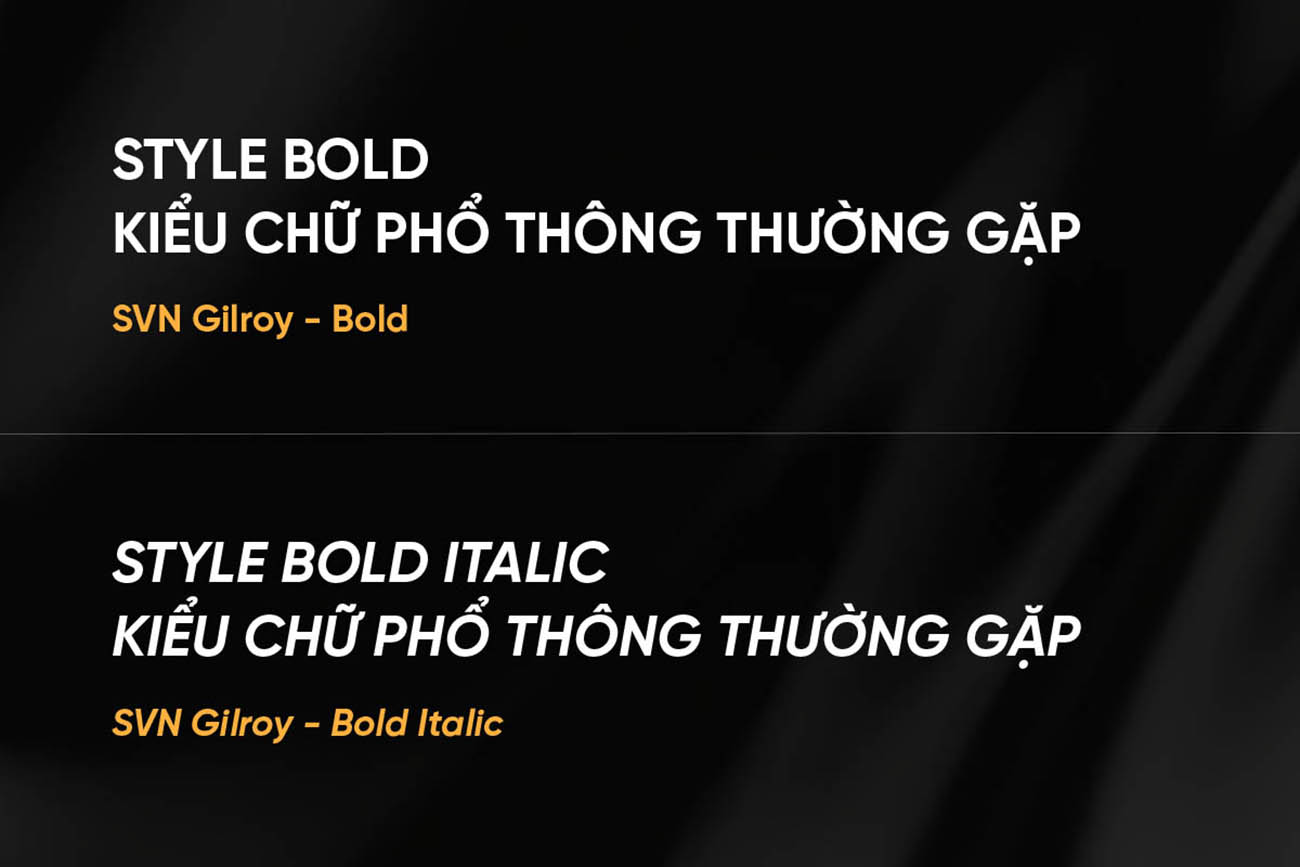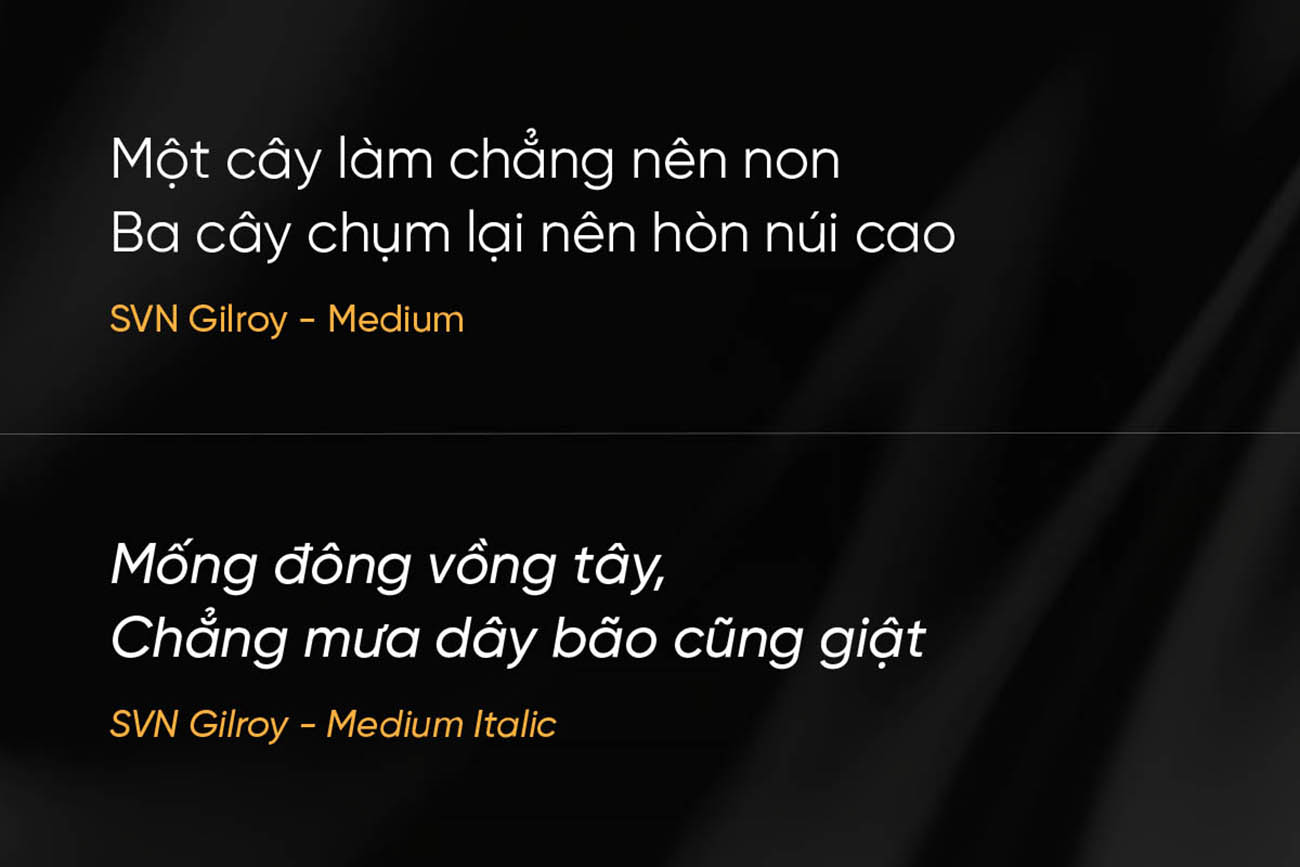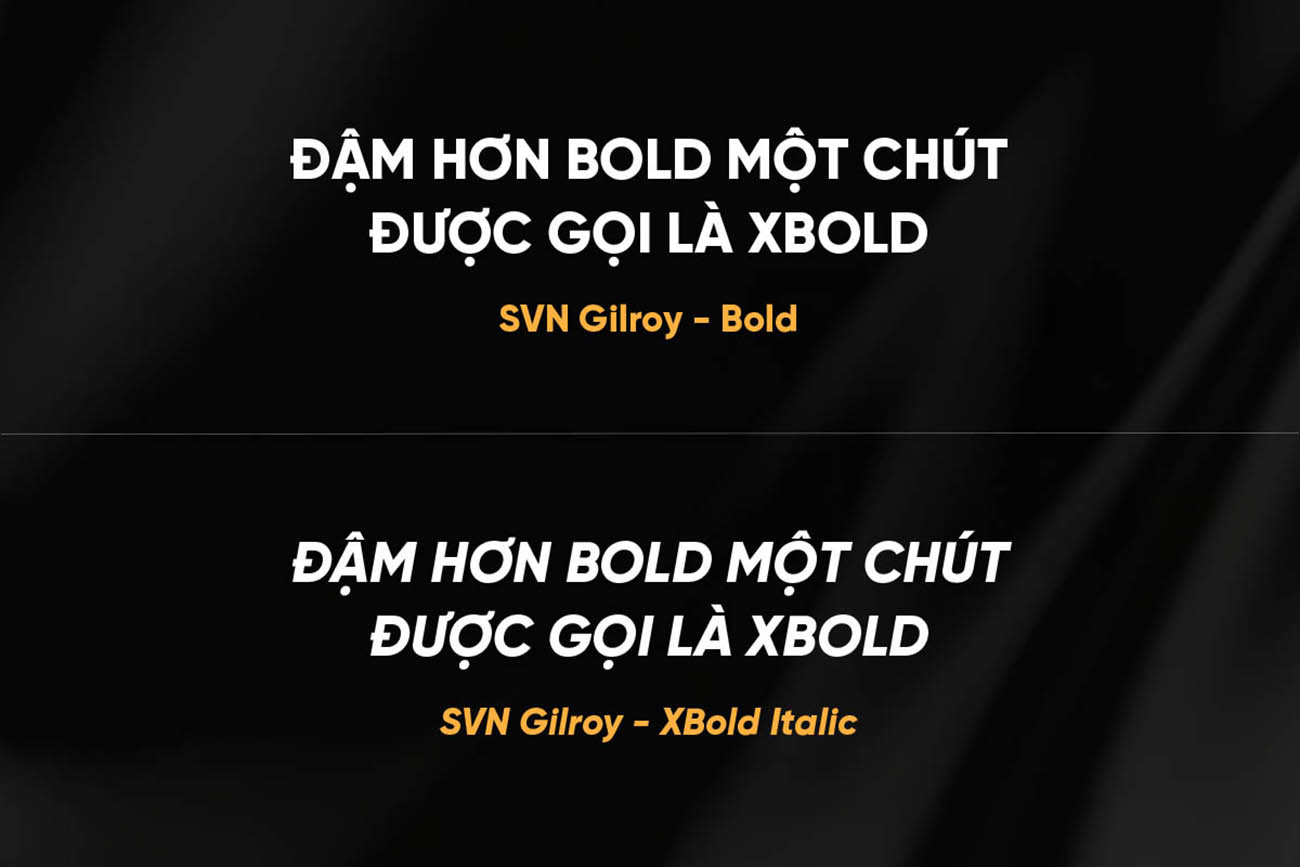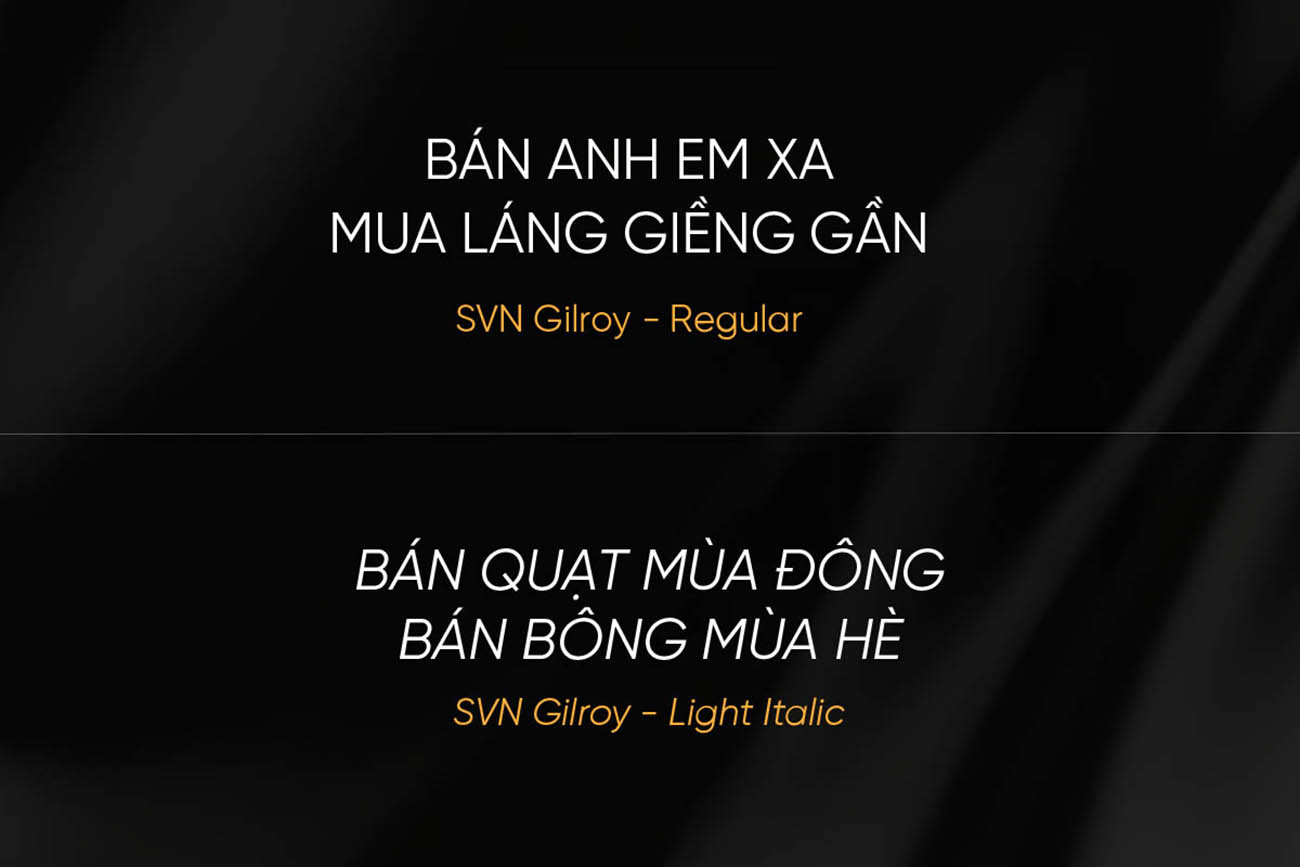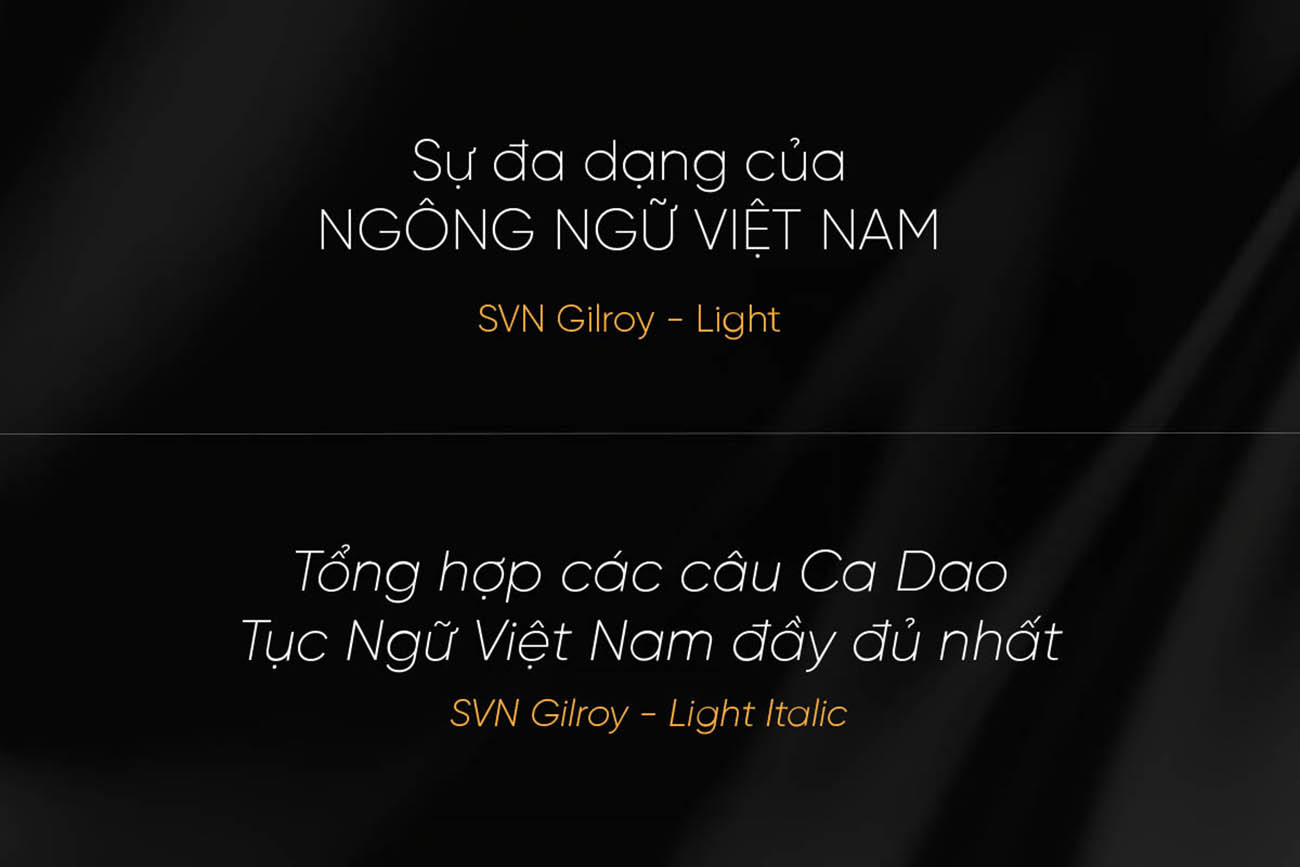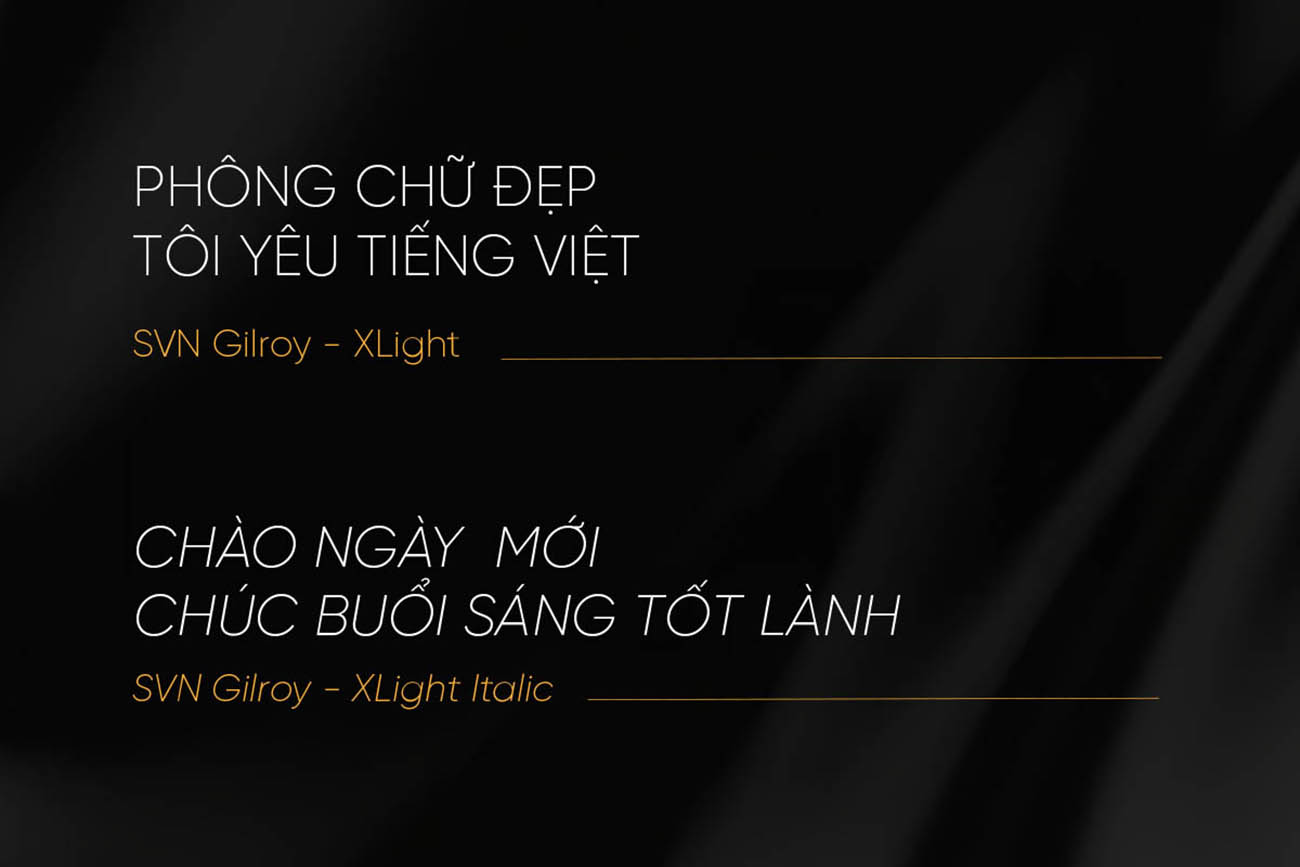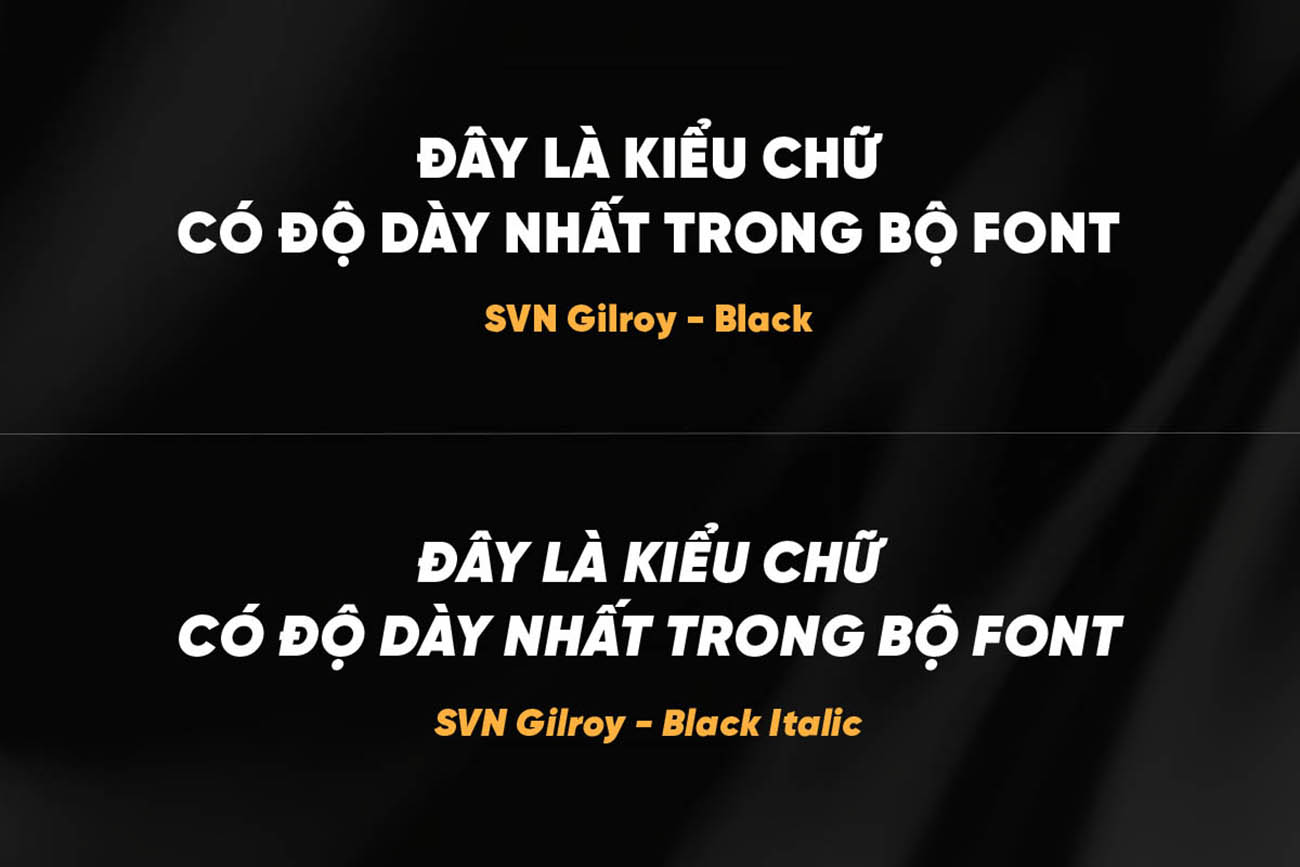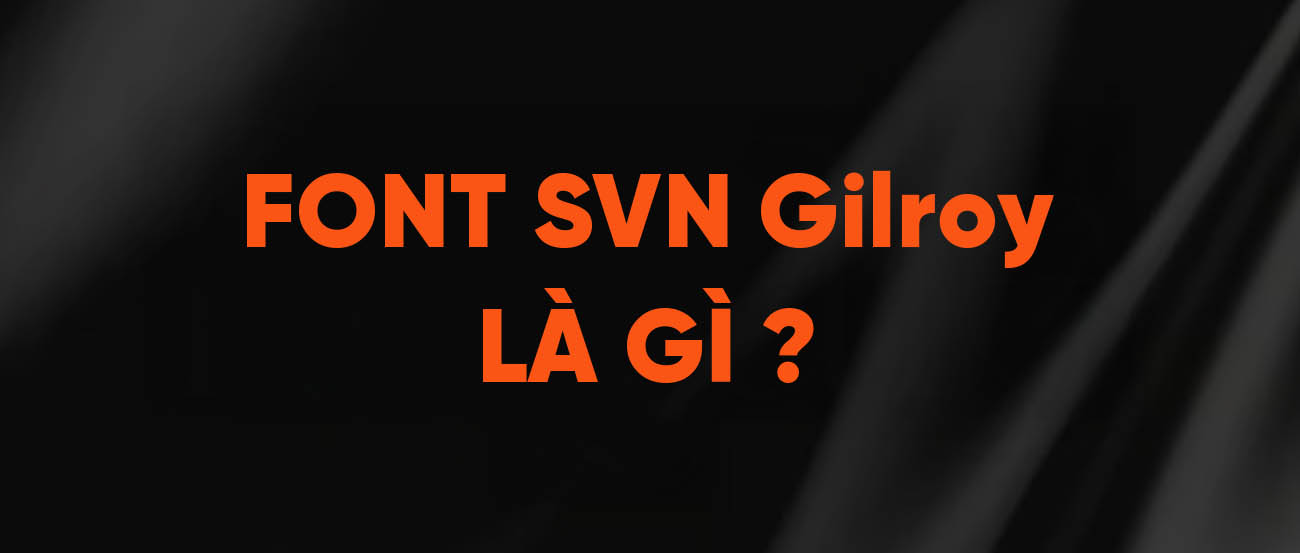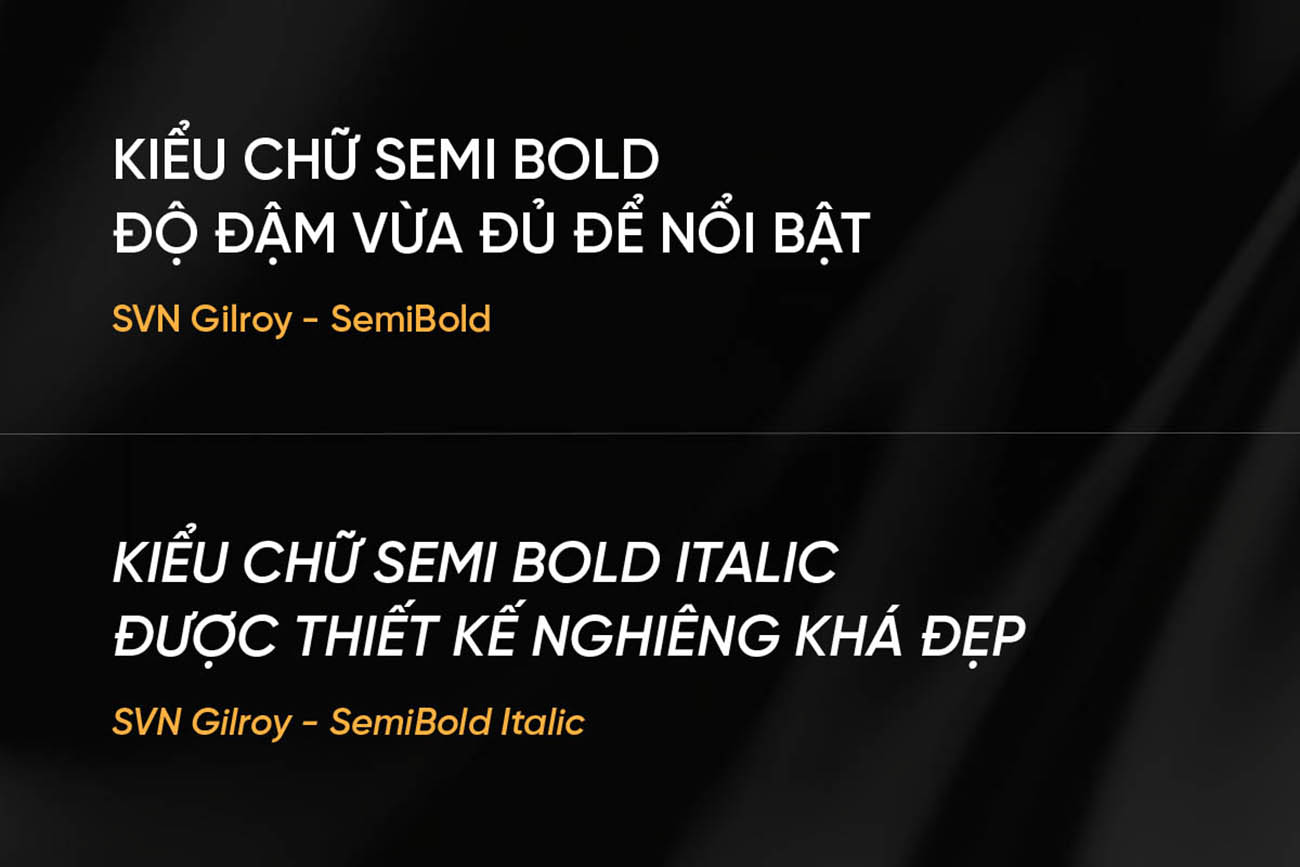
Trong thế giới thiết kế hiện đại, sự đơn giản, tối ưu và dễ đọc luôn là ưu tiên hàng đầu. Font chữ SVN Gilroy – phiên bản Việt hóa của bộ font nổi tiếng Gilroy do Radomir Tinkov thiết kế, chính là lựa chọn hoàn hảo dành cho những ai đang tìm kiếm một font sans-serif hiện đại, cân đối và ứng dụng linh hoạt.
Font SVN Gilroy là gì?
SVN Gilroy là phiên bản Việt hóa của font Gilroy, một typeface sans-serif hình học nổi bật với các đường nét gọn gàng, thân chữ tròn trịa và bố cục dễ nhìn. Font được Việt hóa bởi đội ngũ chuyên nghiệp từ SVN (Styleno.1) – mang lại khả năng hiển thị tiếng Việt hoàn chỉnh, bao gồm đầy đủ dấu và ký tự Unicode.
Với tinh thần thiết kế hiện đại, SVN Gilroy là font lý tưởng cho các ứng dụng công nghệ, thiết kế UI/UX, nhận diện thương hiệu, in ấn và trình bày tài liệu.
Đặc điểm nổi bật của font SVN Gilroy
Font SVN Gilroy nổi bật nhờ thiết kế sans-serif hình học, cân bằng và hiện đại. Bộ font gốc Gilroy gồm 20 kiểu chữ – chia thành 10 trọng lượng chính, mỗi kiểu lại đi kèm với một biến thể Italic tương ứng. Điều này mang lại sự linh hoạt cao trong thiết kế, từ tiêu đề nổi bật đến nội dung nhẹ nhàng.
Dưới đây là chi tiết từng cặp font trong bộ Gilroy gốc – cũng chính là nền tảng cho bản SVN Gilroy Việt hóa:
Gilroy Thin / Thin Italic
Mảnh nhất trong bộ, lý tưởng cho các chi tiết tinh tế, mô tả phụ hoặc thiết kế cần cảm giác nhẹ nhàng, thanh thoát.
Gilroy ExtraLight / ExtraLight Italic
Mỏng hơn Light, dễ kết hợp trong thiết kế mang hơi hướng tối giản, giúp nhấn nhá nhẹ nhàng mà không làm rối bố cục.
Gilroy Light / Light Italic
Cân đối giữa mảnh và rõ nét, thường dùng cho phần mô tả dài, nội dung nhẹ, hoặc các thiết kế mang tính “airy” (thoáng đãng).
Gilroy Regular / Regular Italic
Trọng lượng chuẩn, phù hợp cho văn bản chính, tiêu đề phụ, hoặc các nội dung có độ dài trung bình. Dễ đọc, hiển thị tốt trên cả màn hình và in ấn.
Gilroy Medium / Medium Italic
Nặng hơn Regular một chút, thường dùng để nhấn mạnh nhẹ trong văn bản hoặc đặt cạnh Regular để tạo cấp độ phân biệt trong hệ thống chữ.
Gilroy SemiBold / SemiBold Italic
Trọng lượng đậm vừa, lý tưởng để tạo tiêu đề cấp 2, đánh dấu phần nổi bật mà không quá cứng.
Gilroy Bold / Bold Italic
Dày dặn và mạnh mẽ, phù hợp với tiêu đề chính, call-to-action hoặc logo cần độ nhận diện cao.
Gilroy ExtraBold / ExtraBold Italic
Tạo điểm nhấn cực kỳ rõ ràng. Nên dùng ở kích thước lớn như poster, tiêu đề banner, hoặc thiết kế cần độ tương phản cao.
Gilroy Heavy / Heavy Italic
Cận max-weight trong bộ, cực kỳ đậm và nổi bật. Thường thấy trong các thiết kế branding mạnh, nhấn mạnh một thông điệp ngắn.
Gilroy Black / Black Italic
Trọng lượng nặng nhất. Cực kỳ ấn tượng khi dùng làm tiêu đề lớn hoặc typography nghệ thuật. Nên sử dụng cẩn trọng để không làm rối mắt.
Ứng dụng của font SVN Gilroy trong thiết kế
Với thiết kế sans-serif hiện đại, SVN Gilroy là lựa chọn lý tưởng cho nhiều nhu cầu thiết kế khác nhau. Trong lĩnh vực công nghệ, font này đặc biệt phù hợp để tạo giao diện người dùng (UI/UX), ứng dụng di động, hay trang web nhờ khả năng hiển thị rõ nét và gọn gàng trên mọi kích thước màn hình. Ngoài ra, với các phiên bản đậm – mảnh linh hoạt, SVN Gilroy dễ dàng được sử dụng trong thiết kế logo, bộ nhận diện thương hiệu tối giản và hiện đại.
Trong in ấn và trình bày tài liệu, SVN Gilroy mang lại cảm giác chuyên nghiệp, chỉn chu – phù hợp cho CV xin việc, slide thuyết trình, hồ sơ công ty hay các tài liệu truyền thông nội bộ. Các dự án quảng cáo như banner, poster sự kiện, hoặc bao bì sản phẩm công nghệ cũng có thể tận dụng phong cách hình học, hiện đại và rõ ràng của font này để truyền tải thông điệp một cách hiệu quả. Đây chính là kiểu font dễ sử dụng nhưng vẫn mang lại ấn tượng sâu sắc, phù hợp cả về mặt thẩm mỹ lẫn tính ứng dụng.
Tác giả & phiên bản gốc
Gilroy là bộ font sans-serif hình học được thiết kế bởi Radomir Tinkov, nhà thiết kế đến từ Bulgaria, nổi tiếng với phong cách hiện đại và tối giản. Font được phát hành lần đầu vào năm 2016, gồm 20 kiểu chữ (10 kiểu thẳng và 10 kiểu nghiêng), hỗ trợ hơn 70 ngôn ngữ, sử dụng rộng rãi trong branding và thiết kế kỹ thuật số.
Phiên bản SVN Gilroy do Styleno.1 Việt hóa, giữ nguyên tinh thần thiết kế hình học gốc, đồng thời bổ sung bộ dấu tiếng Việt đầy đủ. Nhờ đó, font vừa đảm bảo tính thẩm mỹ, vừa dễ sử dụng trong các thiết kế tiếng Việt như website, slide, app và nhận diện thương hiệu.
Font SVN Gilroy không chỉ là một lựa chọn thẩm mỹ, mà còn là giải pháp chuyên nghiệp cho những nhà thiết kế yêu thích sự tối giản, hiện đại và hiệu quả. Nếu bạn đang tìm kiếm một font chữ sans-serif Việt hóa dễ dùng, đẹp mắt và đa năng – hãy thử SVN Gilroy ngay hôm nay.